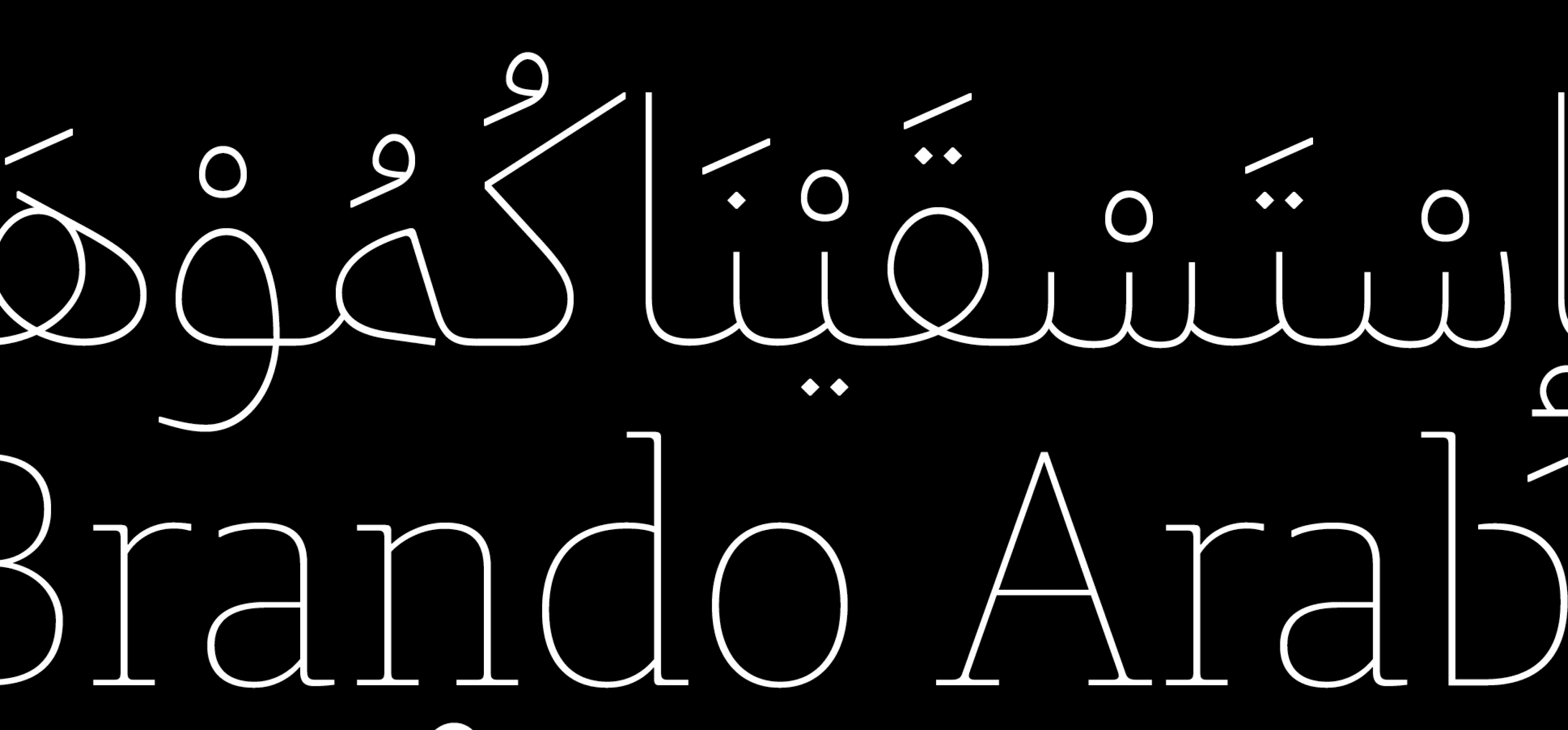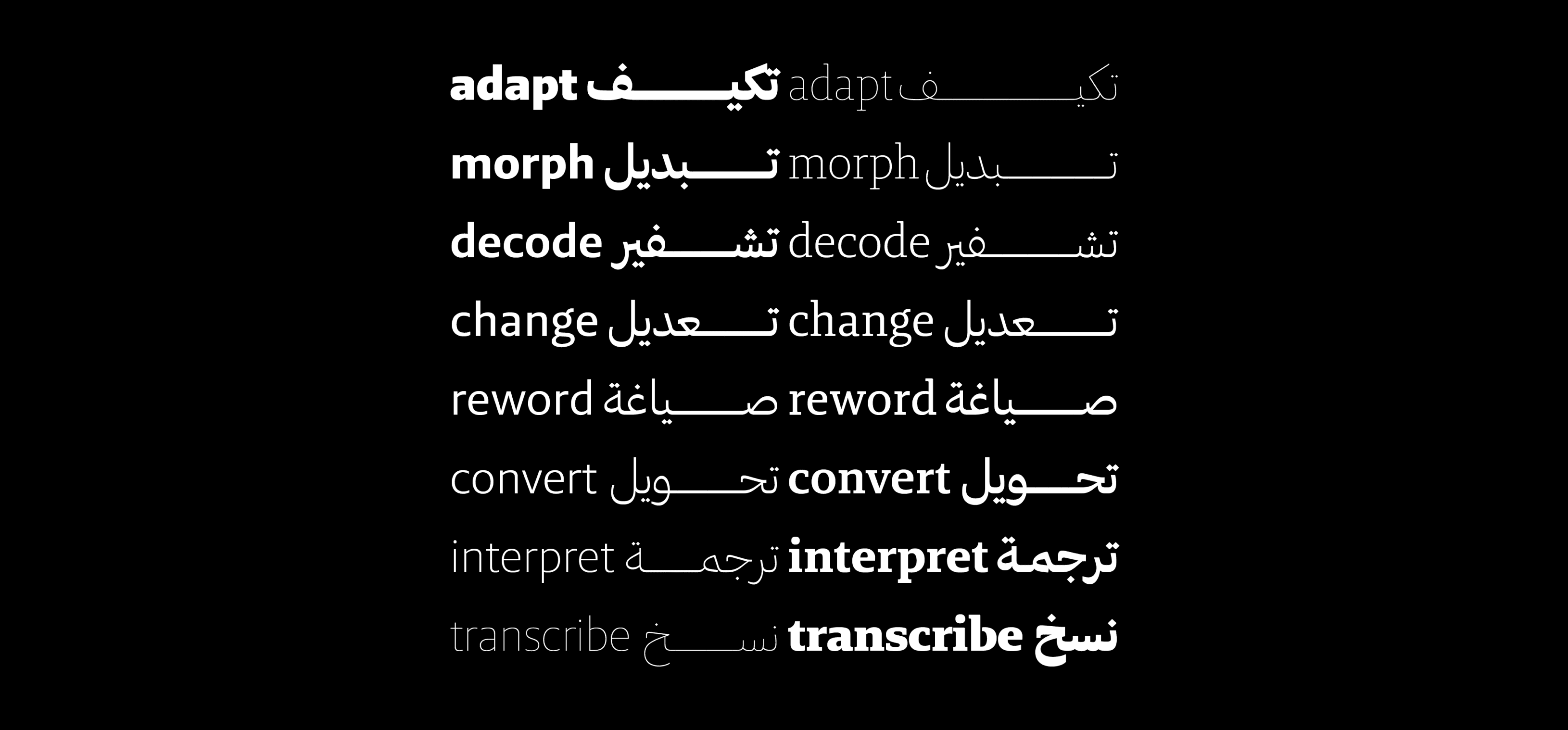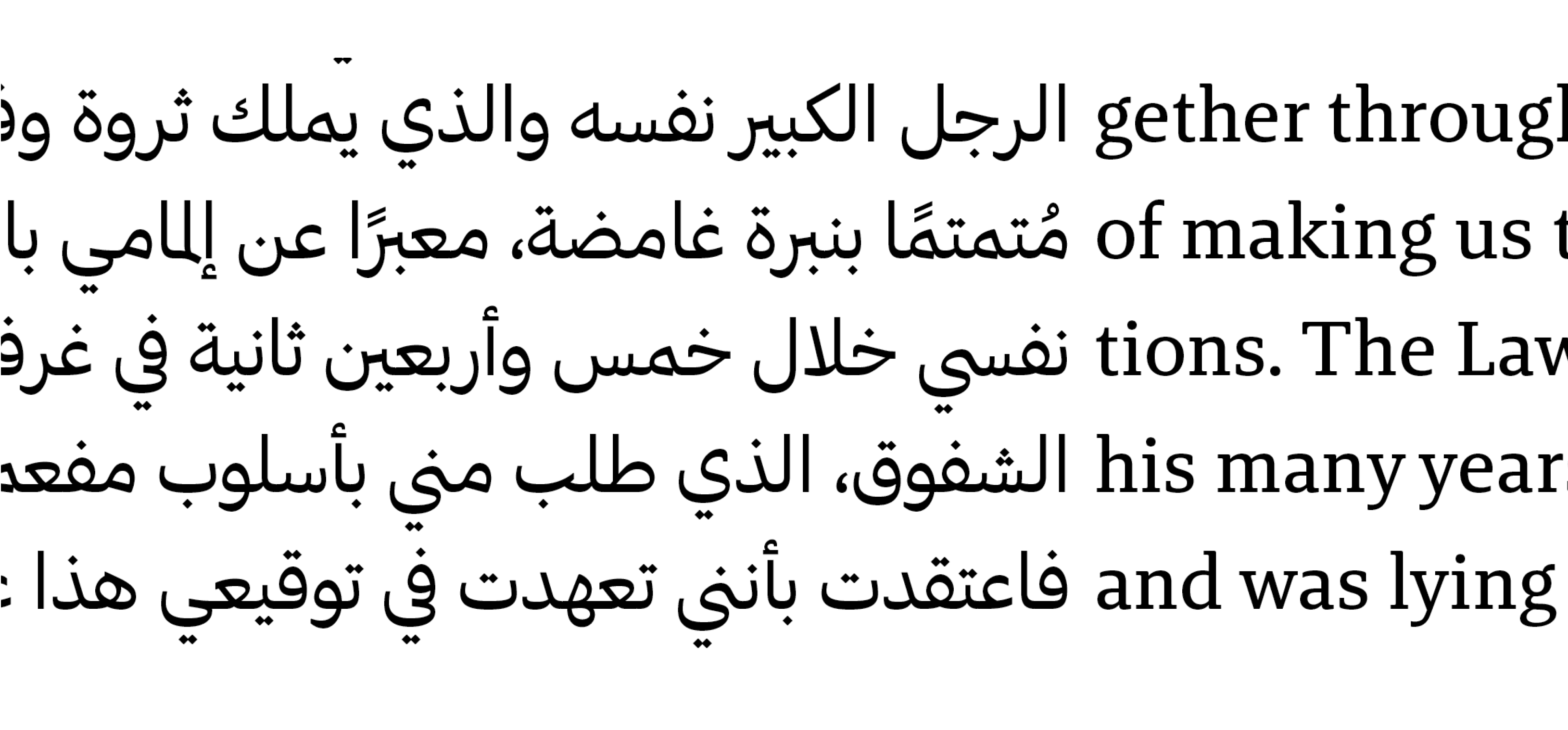
يتبع الخط أسلوب النسخ، وهو نمط من الخط العربي قام الخطاط ابن مقلة في القرن العاشر بتقنينه وجعله معيارًا يُستخدم بشكل رئيسي في الكتابات غير الدينية.
فحتى ذلك الوقت، كانت الحروف العربية تُستخدم أساسًا لنقل النصوص المقدسة.
أما اليوم، فإن أسلوب النسخ يُعد الأكثر استخدامًا في الطباعة والمنصات الرقمية، سواء للأعمال الدينية أو الدنيوية، بفضل وضوحه وسهولة قراءته.